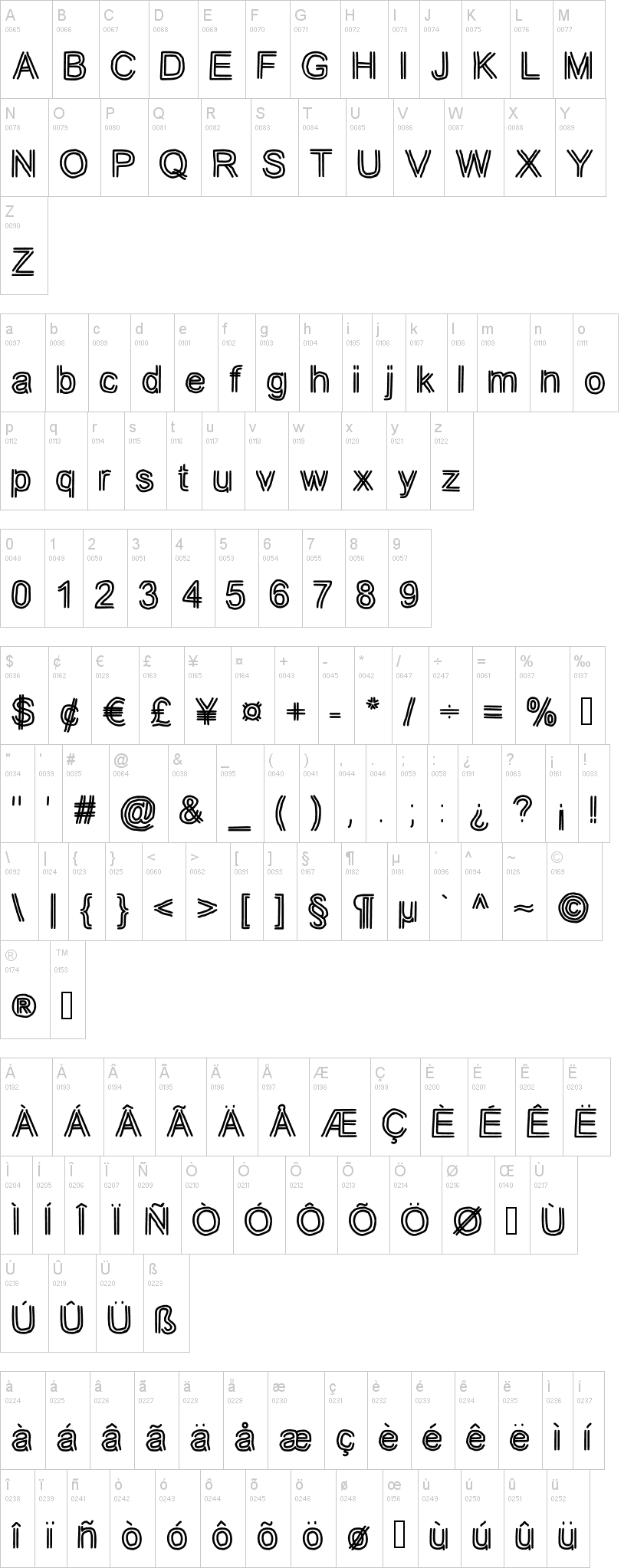
JD Tuline 是由著名的荷兰设计师 Jan Dirk van der Burg 为 JD Design Studio 创作的一款新字体。它是一种现代的、抽象的、多功能的字体,具有良好的可读性和可访问性。它的灵感来源于荷兰的文化和历史,可以在现代和传统的设计当中自由发挥,在多种不同的应用场景中提供统一的视觉体验。它具有非常简单的线条,可以更好地表达抽象的概念,同时还具有良好的可读性和可访问性。内容介绍
JD Tuline是一款非常不错的手写艺术字体,具有很好的视觉感,适合于文化类的宣传设计、商业类品牌的广告和产品包装设计以及个性化文字排版等较多场景。